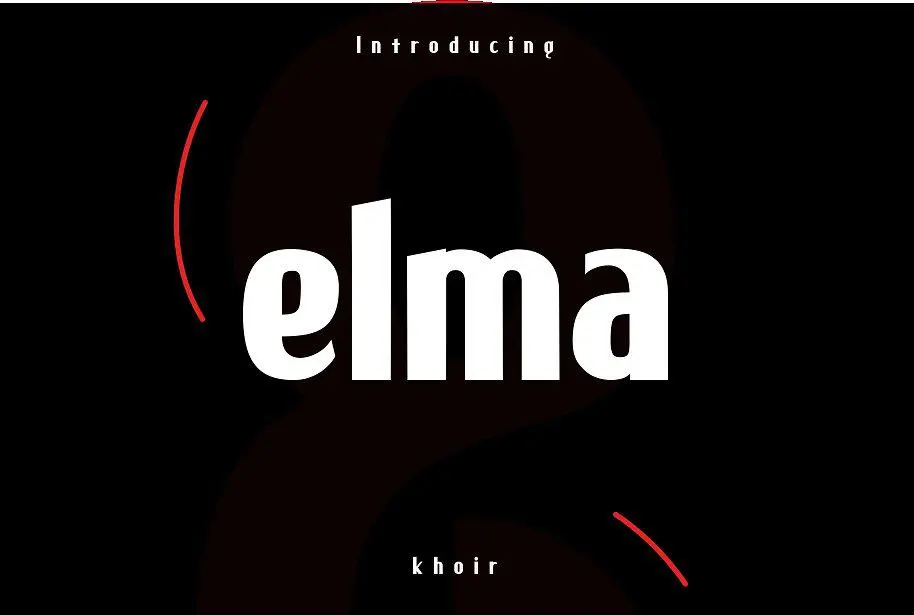
Elma Sans Serif Font – Download Grátis
Introduzimos a fonte Elma. Esta elegante e moderna font foi criada pelo designer Khoir. Elma é uma coleção de três fontes que, juntas, oferecem um amplo leque de aplicações. Cada uma das fontes em sua coleção apresenta características únicas, projetadas para facilitar a criação em diversos formatos. Essas incluem perfis profissionais, posters, logotipos, capas de filmes, cartões de empresa, bilhetes, convites e até mesmo livros, além de muitos outros usos imagináveis. Em sua aplicação, a font Elma simplifica e enriquece o seu projeto. Seja você um designer profissional ou amador, com Elma você pode criar gráficos que expressam elegância moderna sem esforço adicional. Combinada a sua criatividade, ela torna cada trabalho de design mais fluido e versátil. Se proponha experimentar Elma – suas opções são muitas e seus resultados podem ser muito únicos.